Использование различных шрифтов может сделать ваш дизайн более интересным и запоминающимся. Самое главное — умение сочетать.
Благодаря нашей статье вы с легкостью научитесь сочетать несочетаемое и сможете создавать самые уникальные и интересные дизайны. В этой части нашей статьи мы продолжим делиться с вами самыми трендовыми сочетаниями шрифтов.
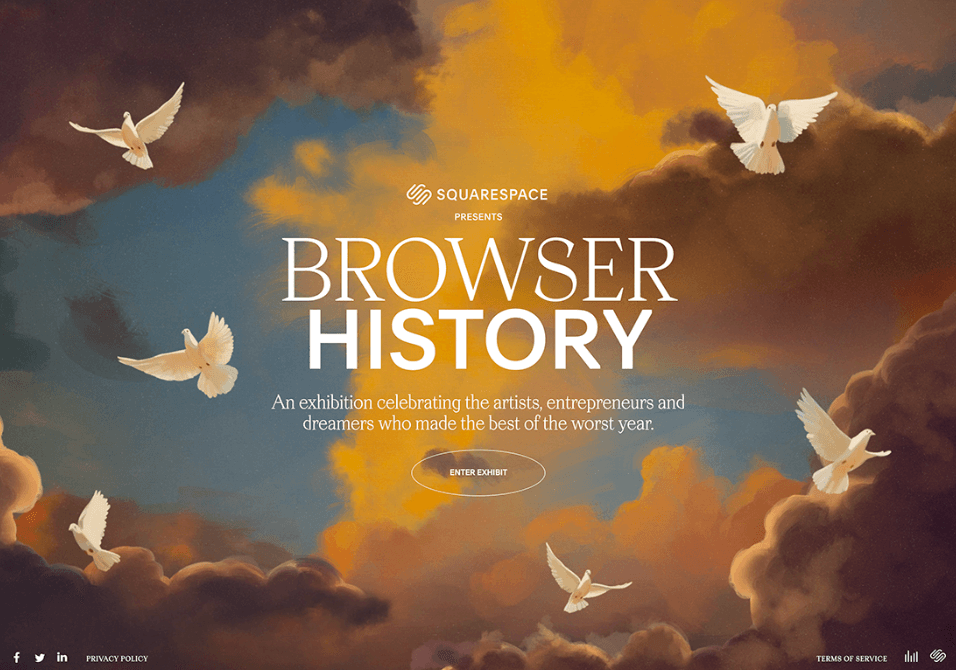
Крупные шрифты отлично работают в паре. Для лучшего эффекта комбинируйте крупный шрифт с засечками с крупным шрифтом без засечек. К дизайну вы также можете добавить еще одну строку меньшего текста, в которой используется один из шрифтов пары.
При использовании этой пары шрифтов мы рекомендуем свести к минимуму другие текстовые эффекты и элементы. Эта комбинация помогает создать интересный эффект многослойности при минимальном количестве шрифтов.
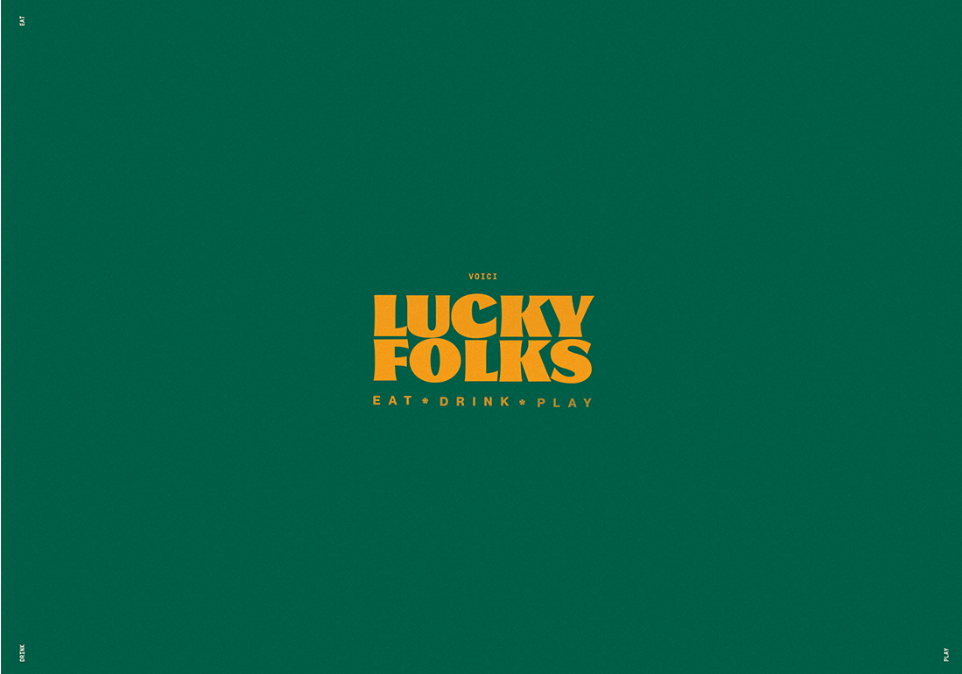
Сочетайте экспериментальные шрифты с любыми нейтральными шрифтами без засечек. При поиске нейтрального шрифта избегайте очень тонких или сжатых шрифтов, потому что они могут снизить индивидуальность экспериментального шрифта.
Если у экспериментального шрифта буквы особой формы, например, округлые — ищите аналогичный нейтральный шрифт с похожей формой, но без засечек. Это усилит воздействие экспериментального шрифта на общий дизайн.
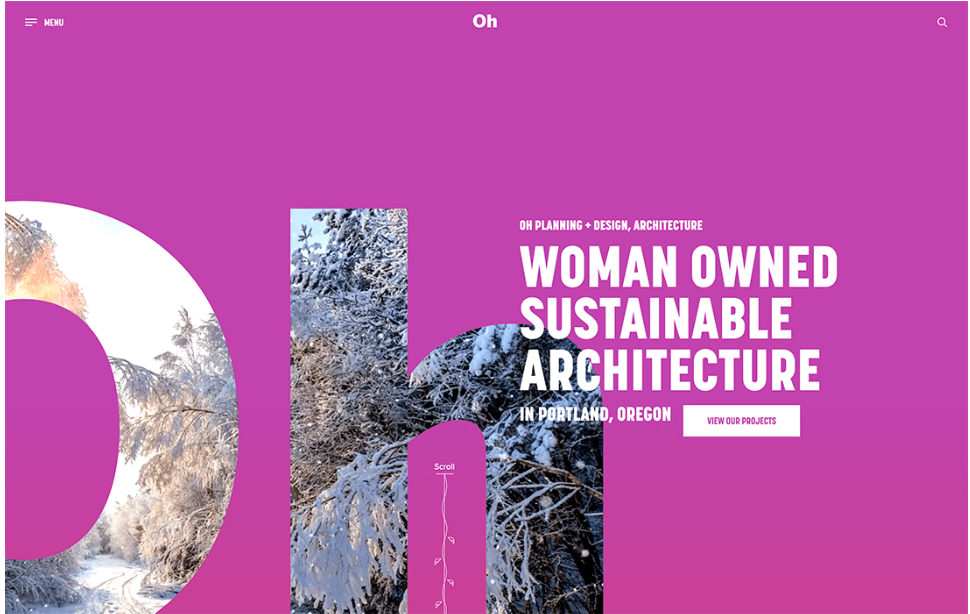
Еще одна тенденция в шрифтовых сочетаниях — это комбинация крупного шрифта без засечек с мелкими шрифтом без засечек для создания многослойного стиля типографики.
Хитрость этой тенденции заключается в том, чтобы использовать простые шрифты без засечек в сочетании с небольшим количеством текста и минимализмом для остальной части дизайна.
На примере выше, благодаря яркому цвету фона, буквы O и H выглядят очень контрастно по сравнению с текстом справа. В сочетании эта многослойность выглядит очень стильно.
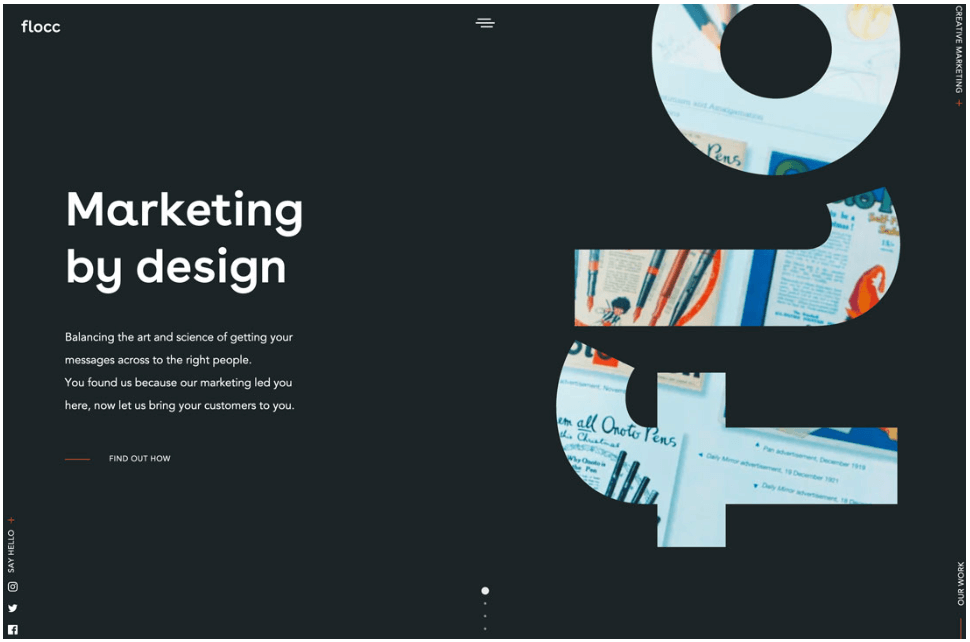
Вы также можете сочетать шрифты разного стиля из одного семейства. Это популярный метод, потому что он облегчает чтение текста на сайте. Кроме этого дизайн выглядит более сбалансированным и гармоничным.
На изображении выше — идеальный пример использования этой тенденции. В одном дизайне соединены различные стили из одного семейства шрифтов — это помогает создать эффектный контраст.
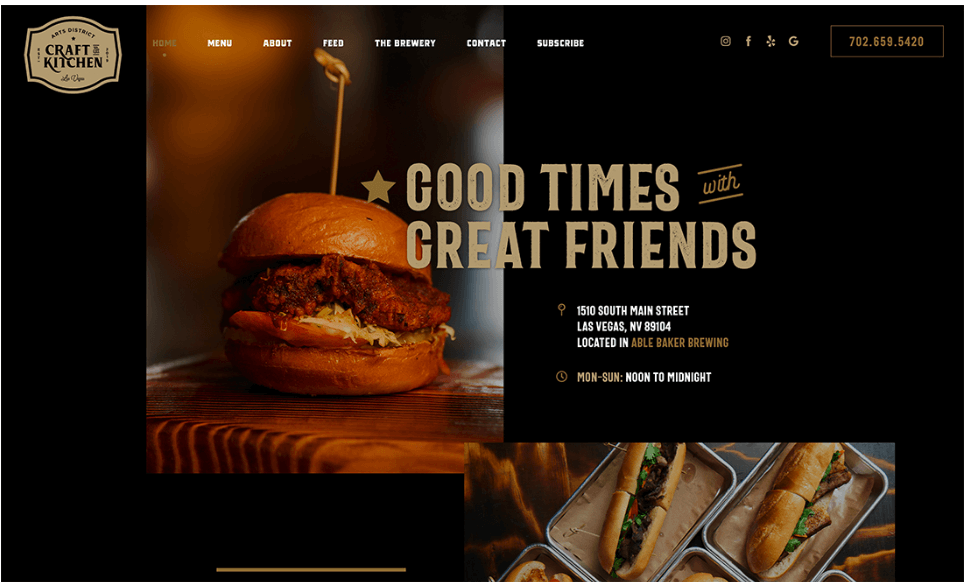
Еще одна тенденция — это сочетание необычного шрифта для основного текста с более мягким шрифтом на фоне. На примере выше основной заголовок выполнен с помощью жирного шрифта с засечками и буквами интересной формы. Кроме того, каждая буква выполнена в необычном стиле, что придает интересную атмосферу общему дизайну.